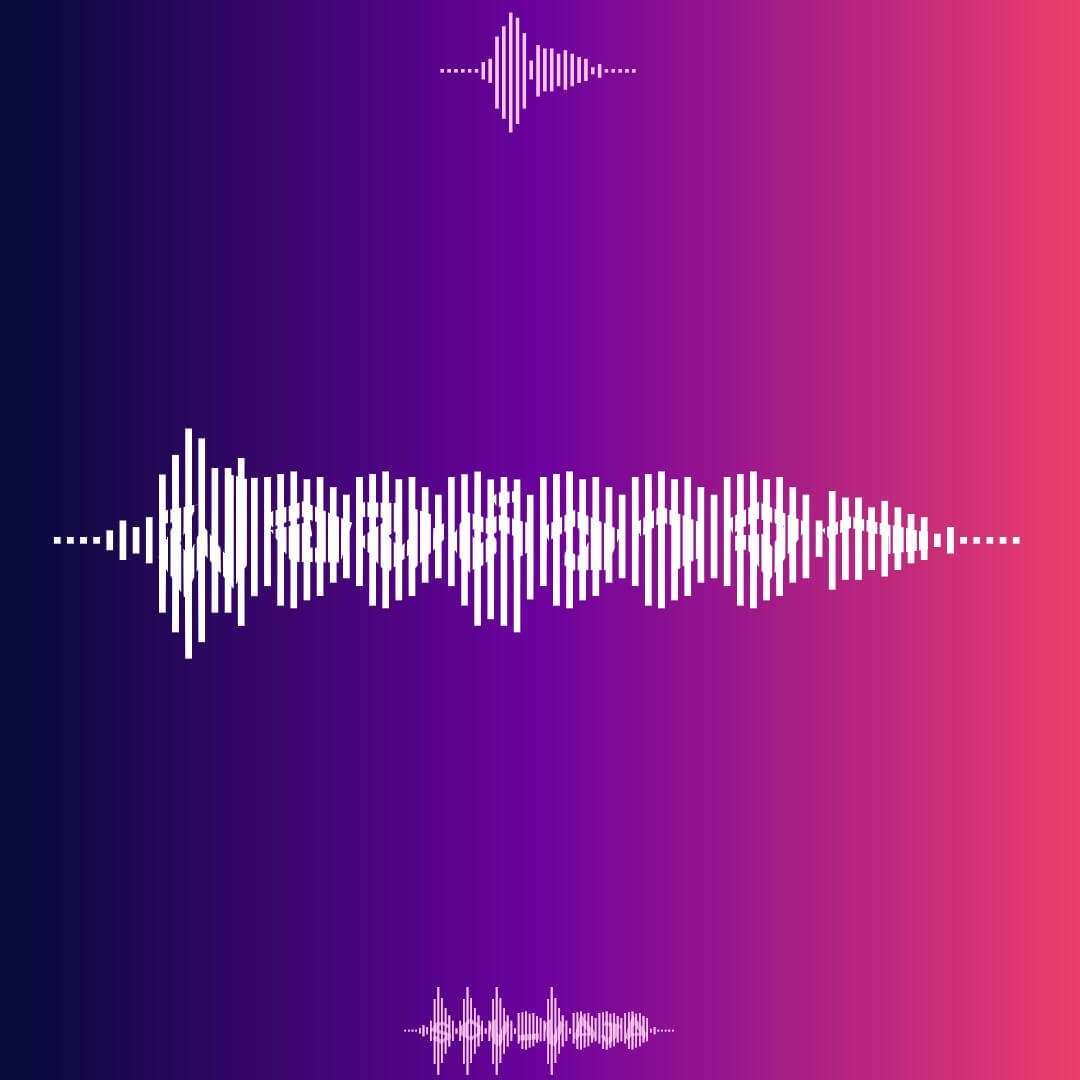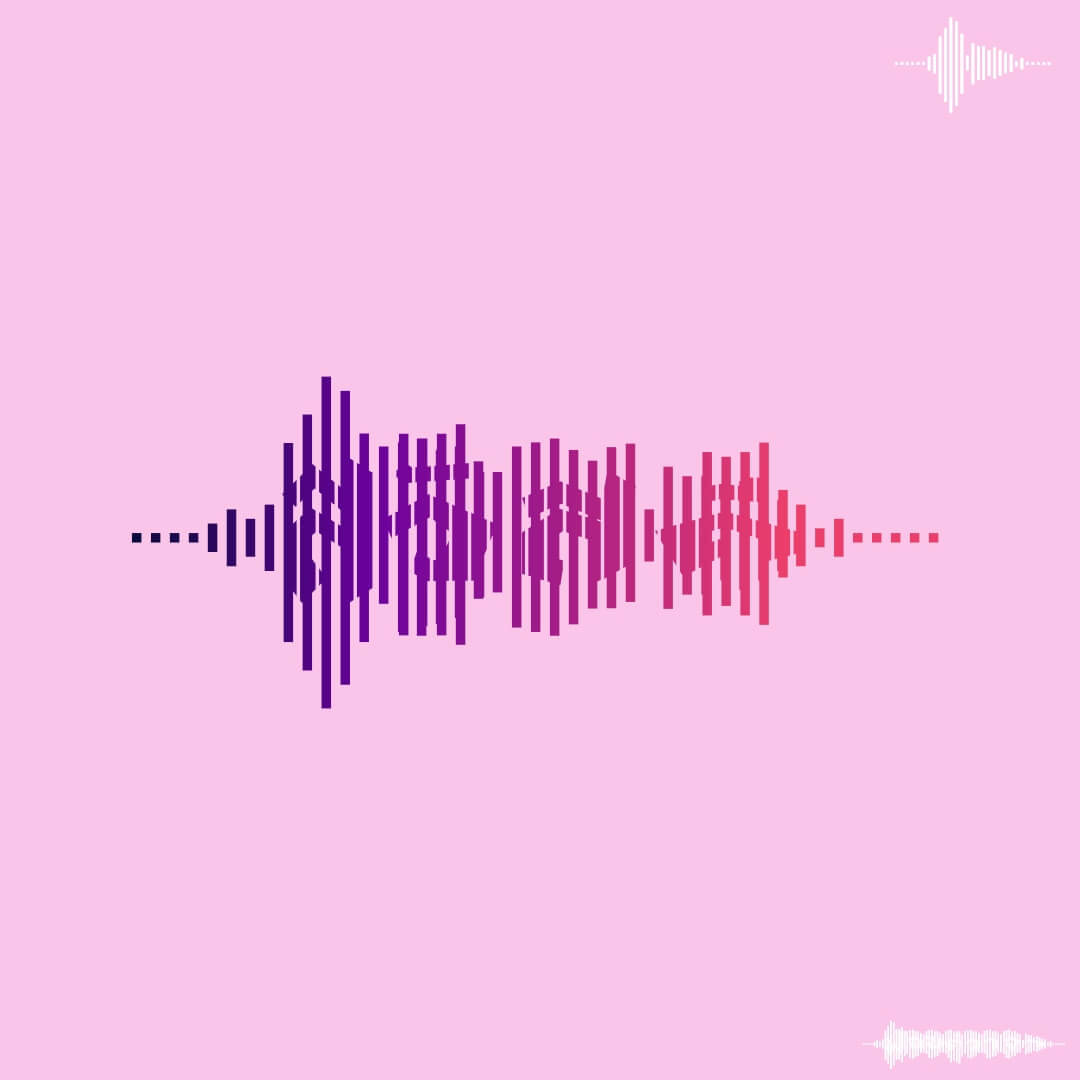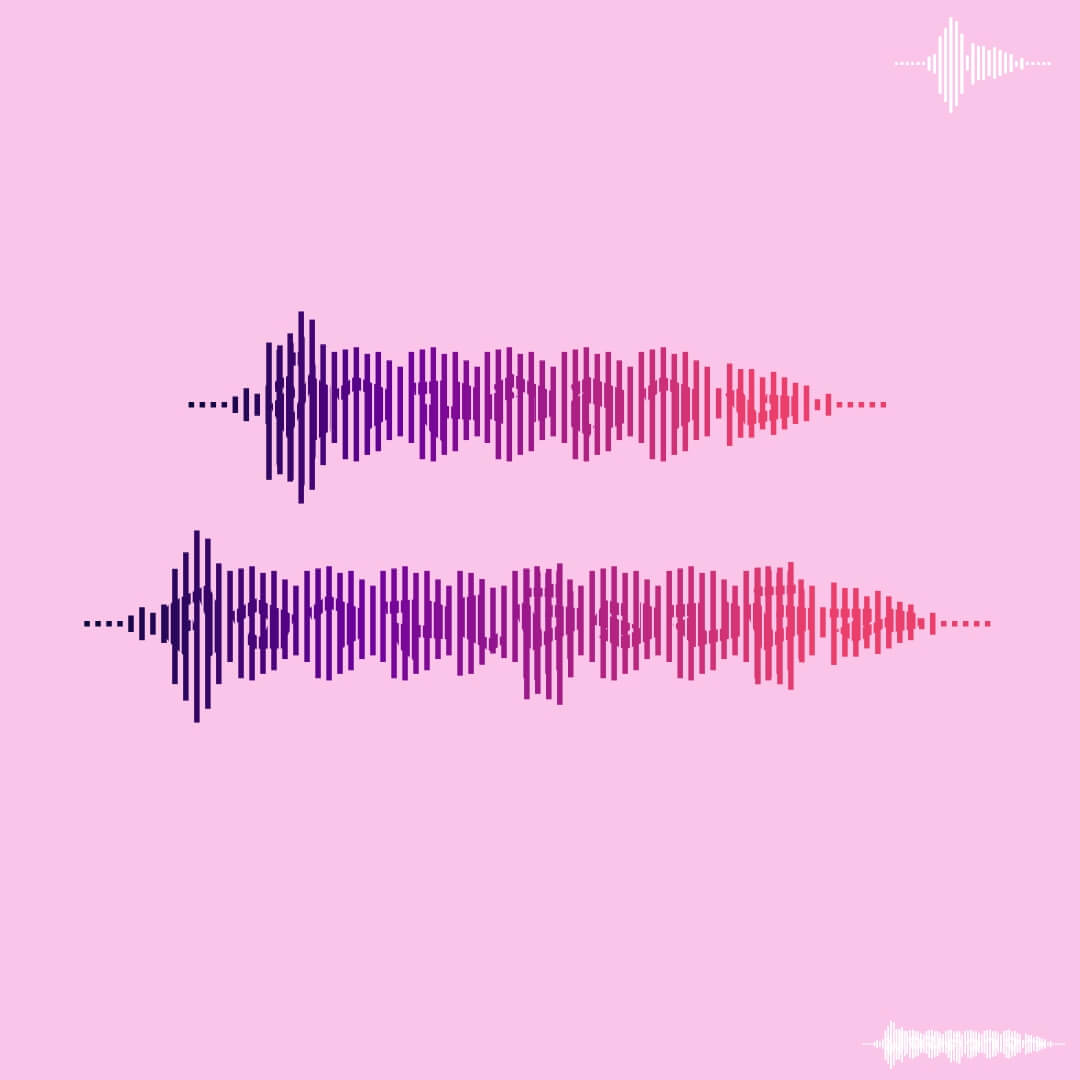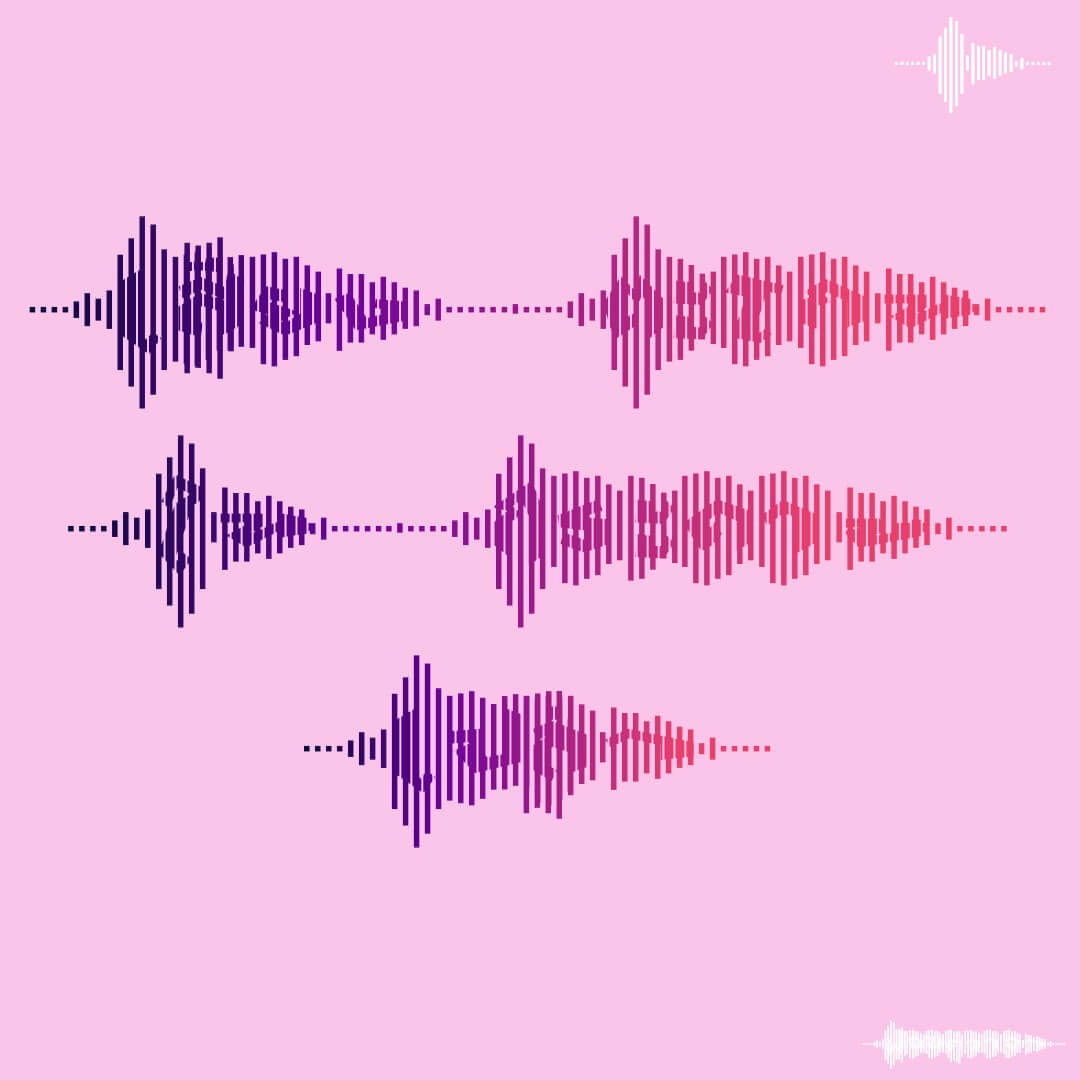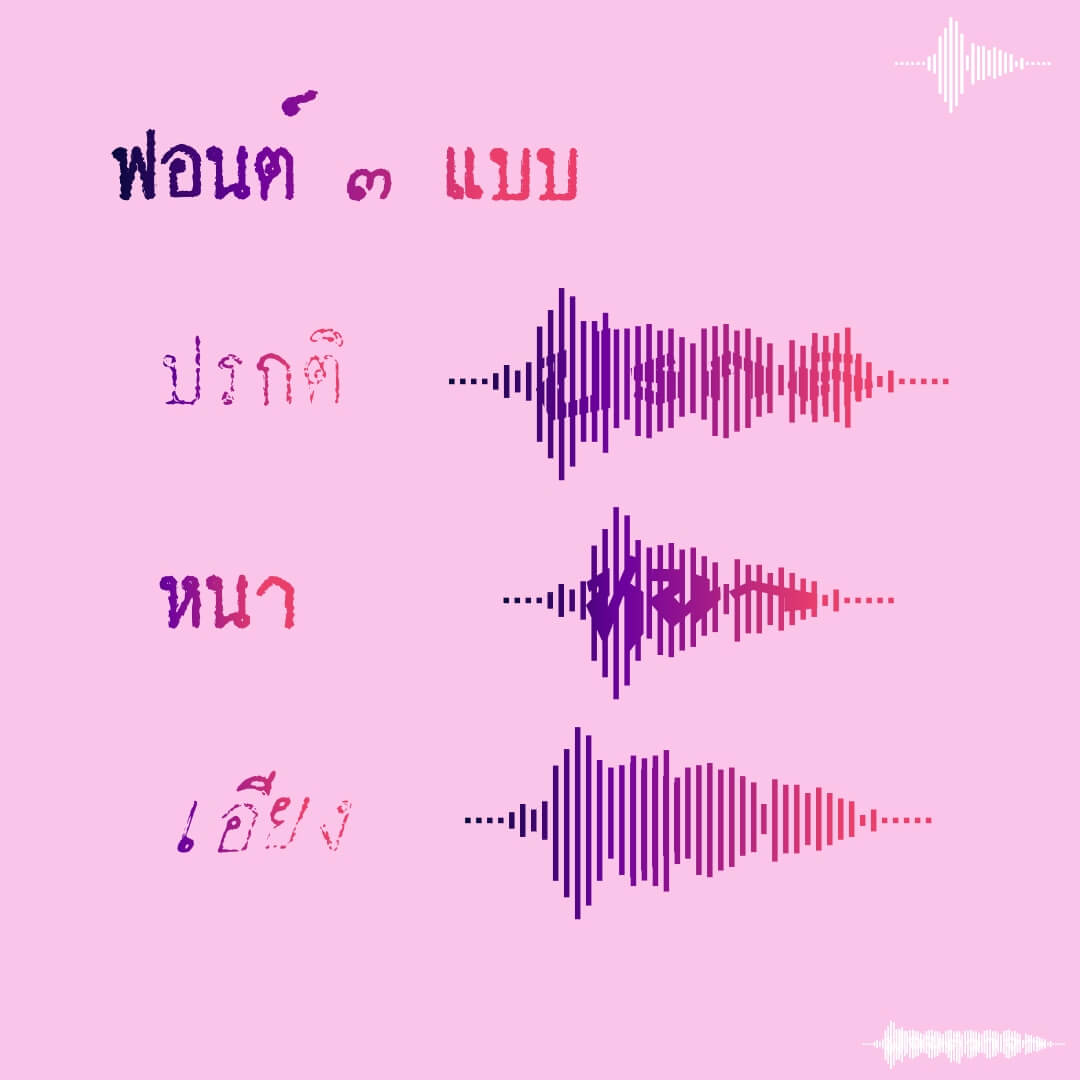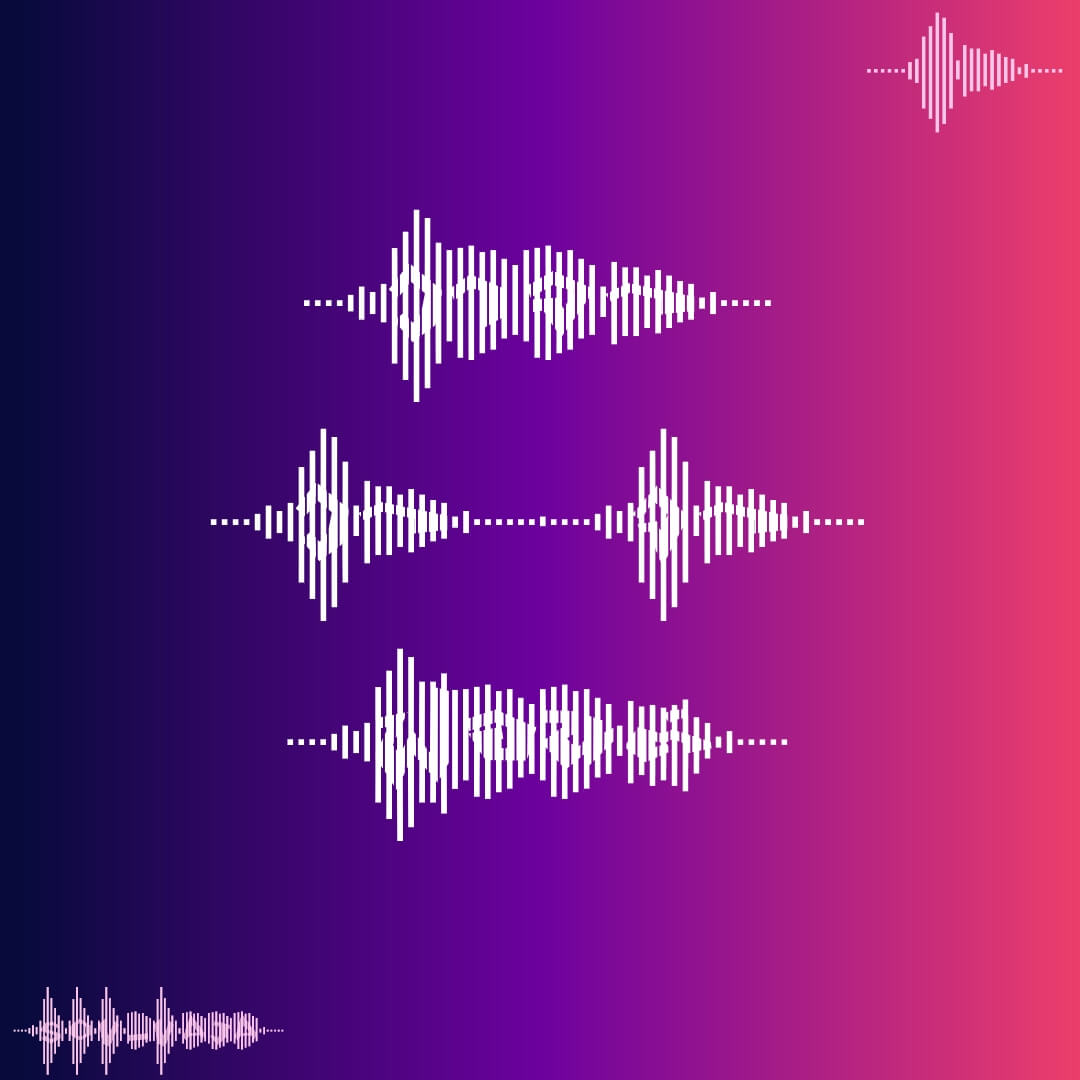
ฟอนต์วาจา – อักษรบนรูปคลื่นเสียง อักษรไทยพิมพ์ได้ปรกติ เว้นวรรคแยกคำหรือประโยค อักษรละตินใส่ไว้ในปีกกา { }
อ่านไม่ออก ใช้ตัวหนา ไม่อยากอ่าน ใช้ตัวเอียง
เบื้องหลังการออกแบบ : ฟอนต์ วาจา
วาจา (SOV_Vaja)